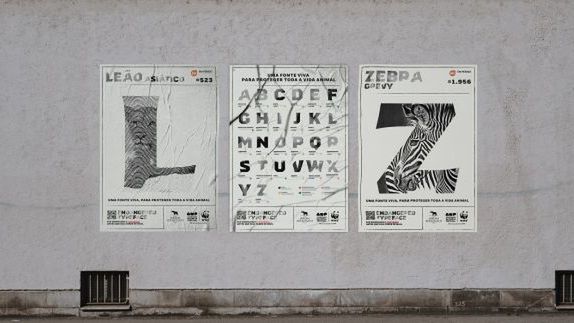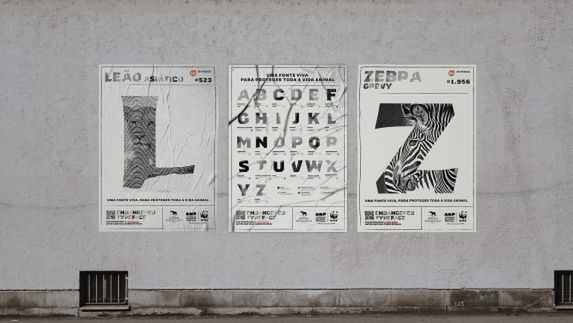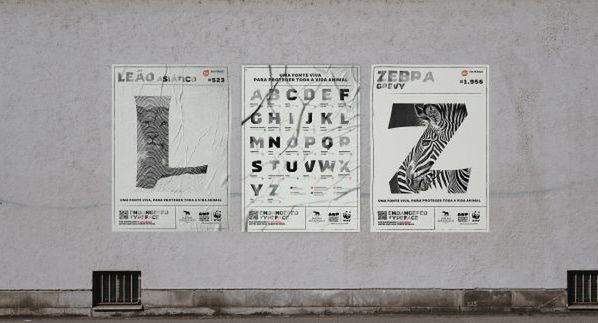
Jak wskazują naukowcy, stoimy w obliczu szóstego masowego wymierania zwierząt. Nasza planeta w alarmującym tempie traci swoją bioróżnorodność i coraz więcej gatunków jest zagrożonych wyginięciem. Aby zwrócić uwagę na ten palący problem środowiskowy i pozyskać fundusze na ochronę umierających gatunków naszej fauny, zespół Ogilvy z Lizbony stworzył specjalną czcionkę typograficzną – Endangered Typeface, której każda z liter reprezentuje dany zagrożony gatunek zwierzęcia.
Czcionka jest bezpośrednio powiązana z bazą danych „Czerwonej księgi gatunków zagrożonych” – publikowaną przez Międzynarodową Unię Ochrony Przyrody (IUCN), która ocenia globalny status zagrożenia wyginięciem wszystkich gatunków na naszej planecie. Jeśli liczba osobników danego gatunku zmniejsza się, kolor czcionki się rozjaśnia, stopniowo niknąc. Każdy z nas może temu przeciwdziałać, wspierając WWF, która wspiera zagrożone gatunki zwierząt. Wystarczy, że wejdziemy na stronę Endangered Typeface i pobierzemy czcionkę, przekazując datek.
Projekt nie tylko pozwala nam śledzić skalę zmian, jeśli chodzi o liczbę zagrożonych wymarciem osobników danego gatunku, lecz także jest użyteczny w naszej codziennej pracy. Aby rozpowszechnić akcję, jej twórcy zachęcają do użycia tego kroju pisma w przekazywaniu informacji o akcji dalej, by zaangażowała w pomoc więcej ludzi, którym leży na sercu dobro planety.
„Tą kampanią w prosty i jednocześnie wyrazisty sposób mogliśmy szeroko przedstawić alarmującą liczbę gatunków zwierząt na skraju wyginięcia. Tym, co chcieliśmy osiągnąć dzięki temu projektowi, jest skłonienie ludzi do przemyśleń oraz do wspierania i rozpowszechniania wiedzy o tym problemie – bo jest on bardziej znaczący, niż nam się wydaje” – mówi Miguel Ralh, CEO BAR Ogilvy.